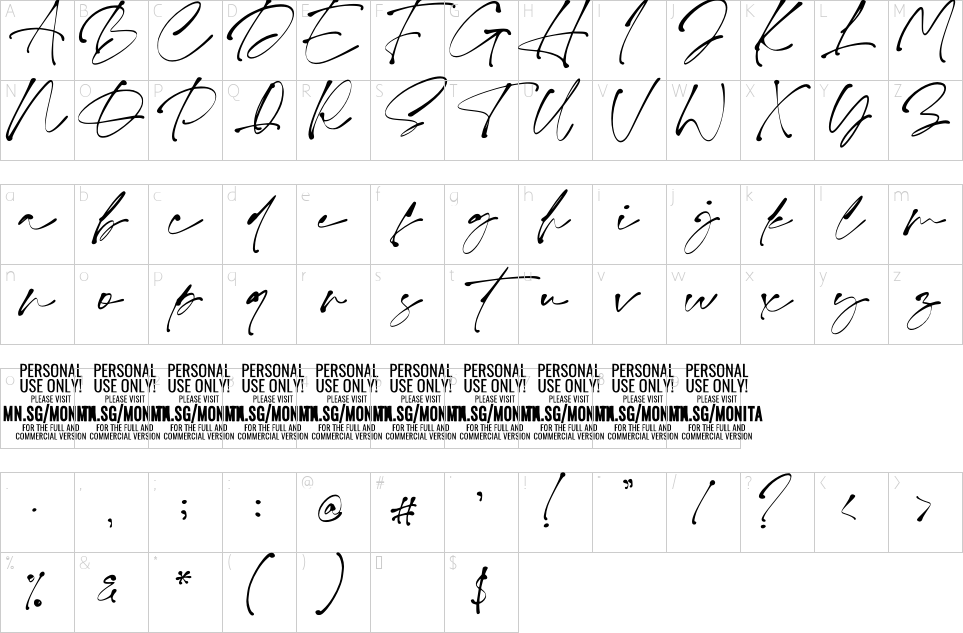
Monita Signature Font | 1001 Free Fonts – Download Grátis
Descubra a elegância e a sofisticação da Monita Signature font, uma opção gratuita e de alta qualidade para seus projetos digitais. Desenvolvida por Måns Grebäck, essa fonte se destaca pela sua perfeita combinação de modernidade e elegância, perfeita para qualquer aplicação, desde design editorial até criação de logotipos. Com uma fácil aplicação em ambientes Windows e Mac, a Monita Signature oferece uma experiência de uso fluida e intuitiva que complementa perfeitamente seu design. Esta é uma excelente escolha para quem busca uma fonte de qualidade sem comprometer seus orçamentos, e já são mais de 150 usuários satisfeitos que provaram o seu valor. Não perca mais tempo, descubra a Monita Signature e inove na forma como você apresenta seu trabalho.